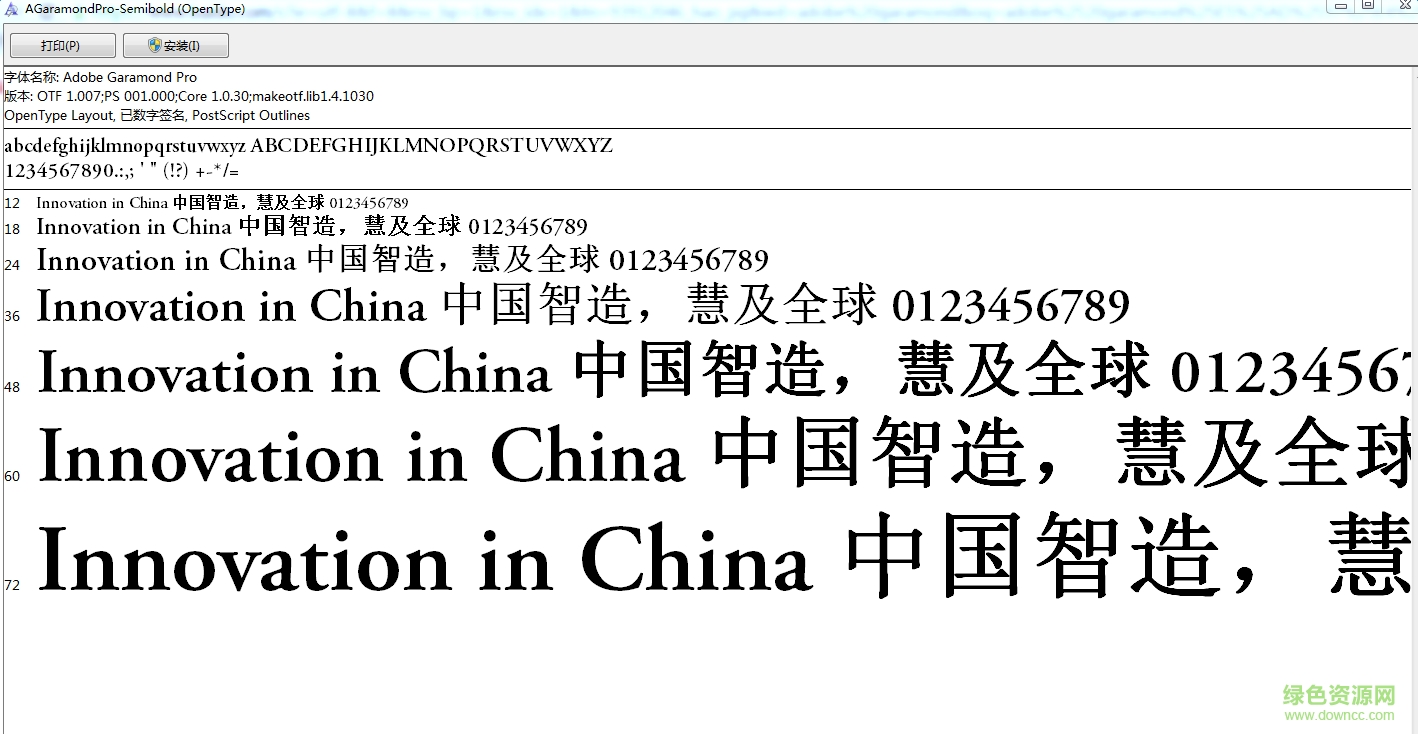
adobe garamond pro bold粗體
adobe garamond pro bold是什么?adobe garamond pro bold是一款a常用于adobe設(shè)計軟件中的粗體字體,字形清晰易讀,勾角自然,整體舒展醒目,小編為大家打包好了,解壓復(fù)制即可使用,快來下載吧!